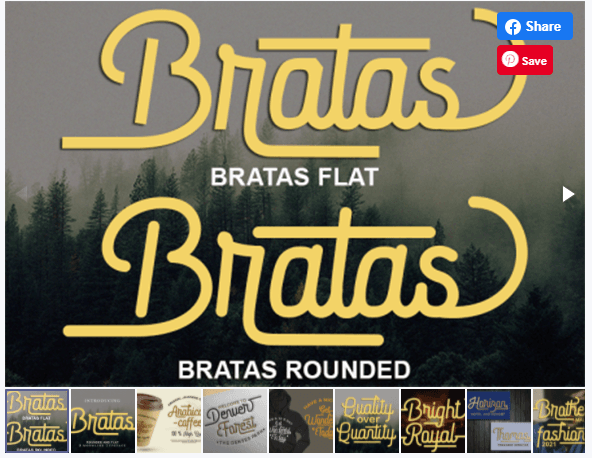
Bratas Font
Bratas - красивый рукописный шрифт в винтажном стиле. Этот шрифт был специально разработан для тех, кому нужен красивый и освежающий вид своего дизайна.